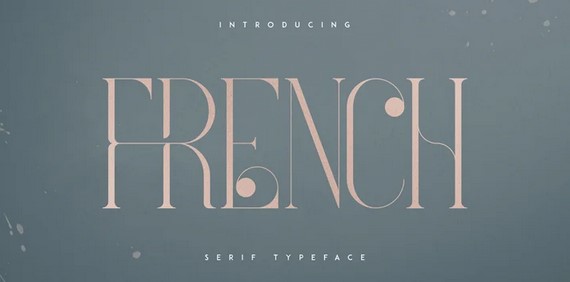
[Myfonts] French VP Font (2021)
Представляем вашему вниманию шрифт French Serif Typeface
French - это роскошный, чистый шрифт, состоящий из 4 шрифтов, которые очаруют ваш следующий проект. Они имеют множество альтернативных глифов, лигатур и многоязыковую поддержку. Очень универсальный шрифт, который отлично работает в больших и малых размерах.
French идеально подходит для проектов брендинга, дизайна домашней утвари, упаковки товаров, заголовков журналов - или просто как стильное наложение текста на любое фоновое изображение.
Прописные цифры, пунктуация и символы
Светлый
Обычный
Полужирный
Черный
Альтернативные глифы
Лигатуры
Многоязыковая поддержка